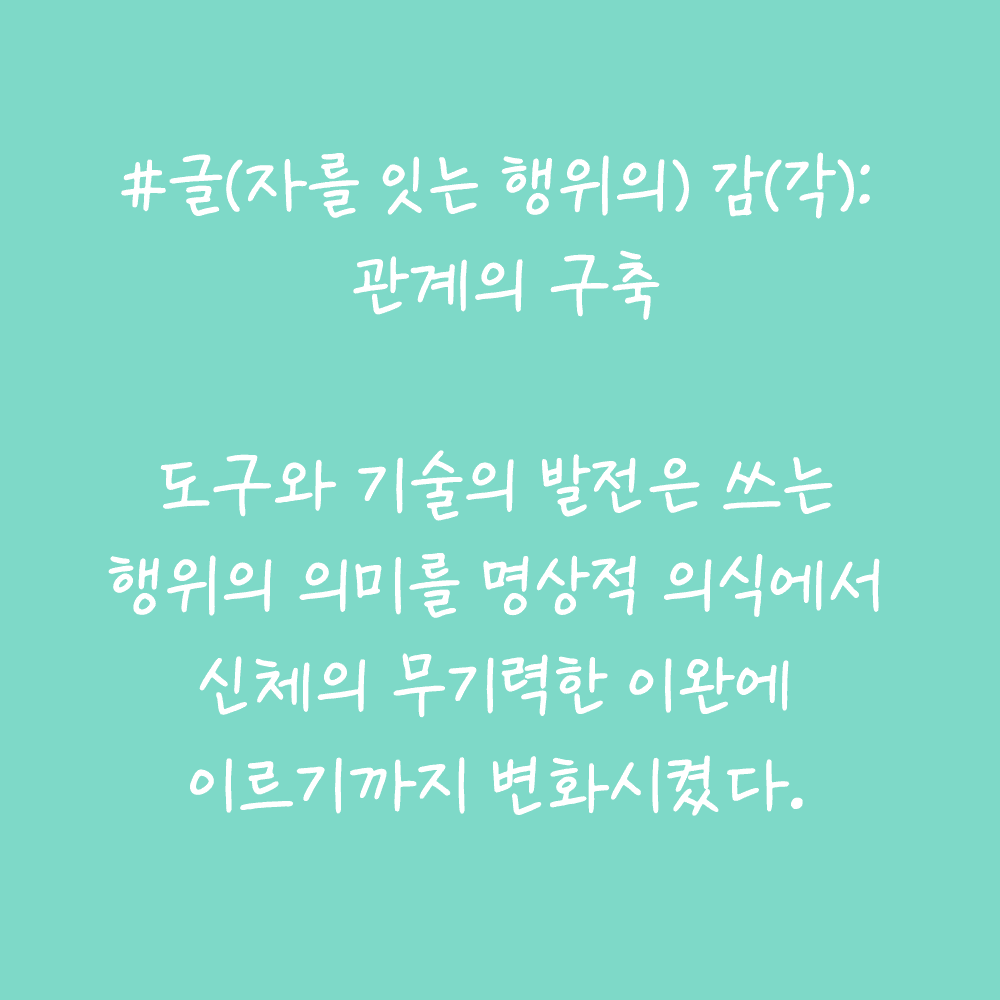
그리운X국한박 글방구리체
GriunXHangeul Banguri
그리운X국한박 글방구리체 소개
제5회 한글실험프로젝트 《글(자)감(각): 쓰기와 도구》 The 5th Hangeul Design Project 《Senses of Writing: Tools & Perception》 전시기간: 2025.11.19.~2026.3.22. 전시장소: 문화역서울284 RTO 주최·주관: 국립한글박물관 이 손글씨 폰트는 국립한글박물관 제5회 한글실험프로젝트 《글(자)감(각): 쓰기와 도구》 전시 연계 이벤트를 통해 제작되었습니다. 손의 움직임과 쓰는 감각을 그대로 담아, 쓰기의 경험을 폰트로 확장합니다.